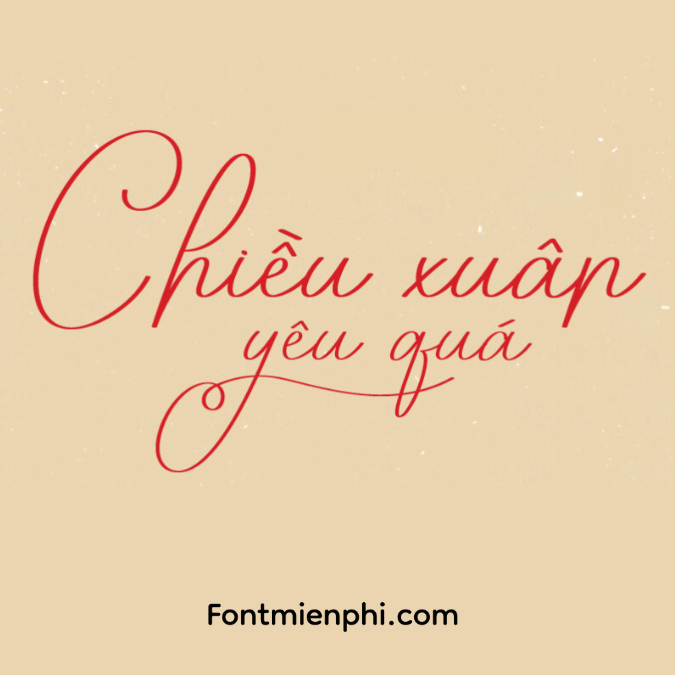
FONT VIỆT HÓA 1FTV VIP DAUGHTER
“Nét chữ dịu dàng – Tình yêu của Mẹ”
ĐẶC ĐIỂM NỔI BẬT
‍ Phong cách Handwritten ấm áp: Nét chữ mềm mại như chính bàn tay mẹ viết cho con
Họa tiết trẻ thơ tinh tế: Điểm xuyến hình sao, mây, bóng bay cách điệu
✍️ Chất viết tay tự nhiên: Độ nghiêng và đậm nhạt biến đổi như thật
ỨNG DỤNG Ý NGHĨA
• Thiệp sinh nhật cho bé
• Album ảnh gia đình
• Quà tặng handmade
• Decal trang trí phòng bé
• Bao bì sản phẩm cho mẹ và bé
“Daughter – Gửi gắm yêu thương qua từng con chữ”